汉字的基本印刷字体发源于楷体,成熟于宋体,繁衍出仿宋、黑体及现代的多种字体。我国印刷行业曾长期从日本购入宋体和黑体字模,日本则引进了中国的仿宋体和楷体活字,这种交流使两国印刷字体至今仍保持相近的风貌。
就目前来说,常用的基本印刷字体大致有下面四种:
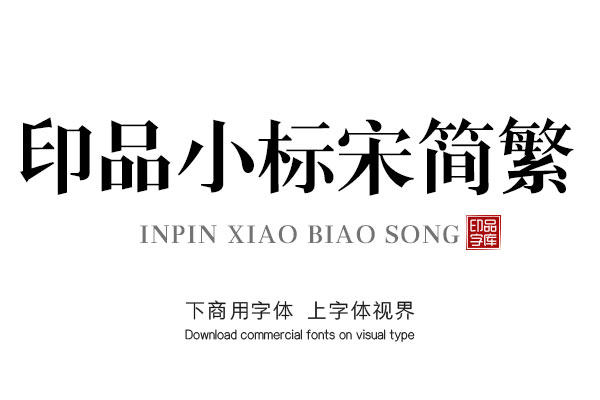
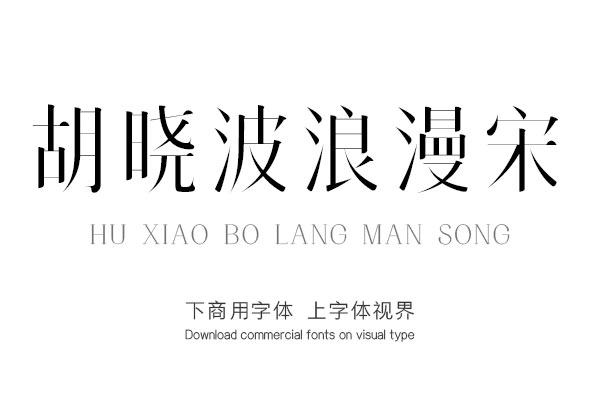
1、宋体的特点
横细竖粗,点如瓜子,撇如刀,捺如扫。它在起笔、收笔和笔画转折处吸收楷体的用笔特点,形成修饰性“衬线”的笔型。
3、仿宋体的特点
虽然与老宋体有些相似,但横竖笔画几乎一致,笔画两端
有毛笔起落的笔迹,竖画直而横画略向右上方上翘3°左右。
4、楷体的特点
是传统的楷书在印刷字体中的延续,它笔迹有力,粗细适
中,字划清楚,易读性很高。